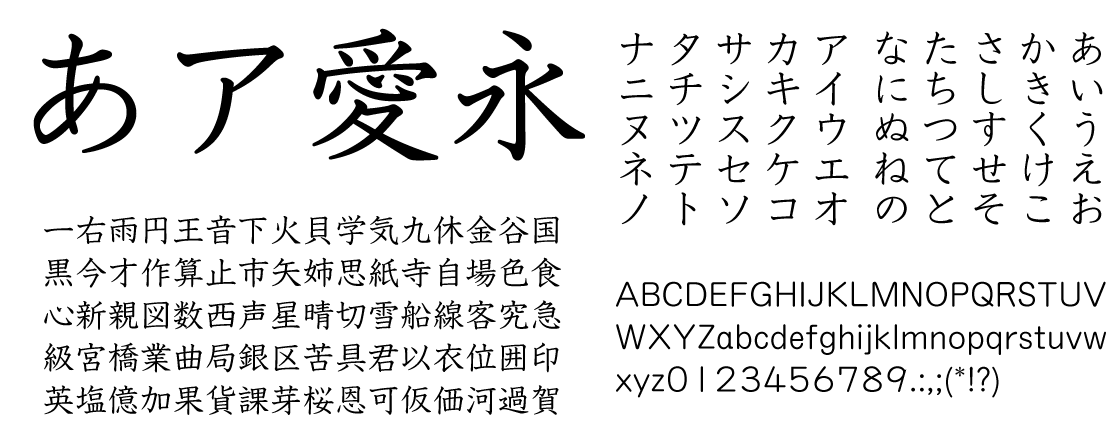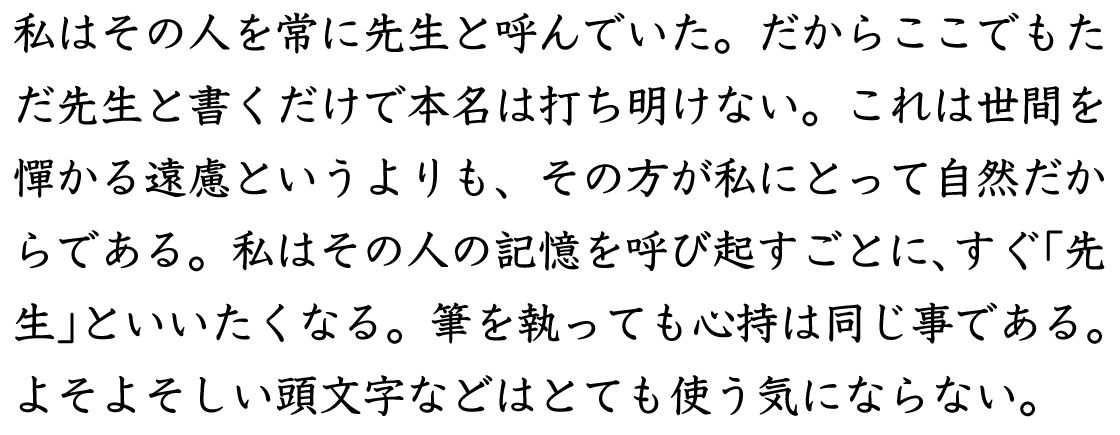
モトヤ教科書
書体解説
教科書体は横画(おうかく:横線)が肩上がりになっています。この角度が一文字の中でも、全文字を通じても揃っていなければなりません。例えば「三」という文字は、上の方から終筆に向かって、徐々に角度を浅くしており、これが横画を視覚的に揃える時の重要な技術です。モトヤは正楷書の制作以来、この技術を継承し研鑚してきました。教科書体もこの技術を十分に発揮し制作していますので、硬筆の力強さと楷書風の柔らかさを表現しながら、安定感あふれる読みやすい書体となっています。
モトヤ教科書2
モトヤ教科書3
モトヤ教科書4